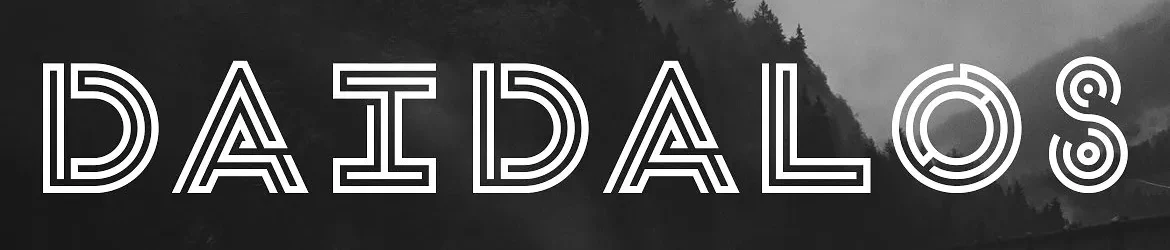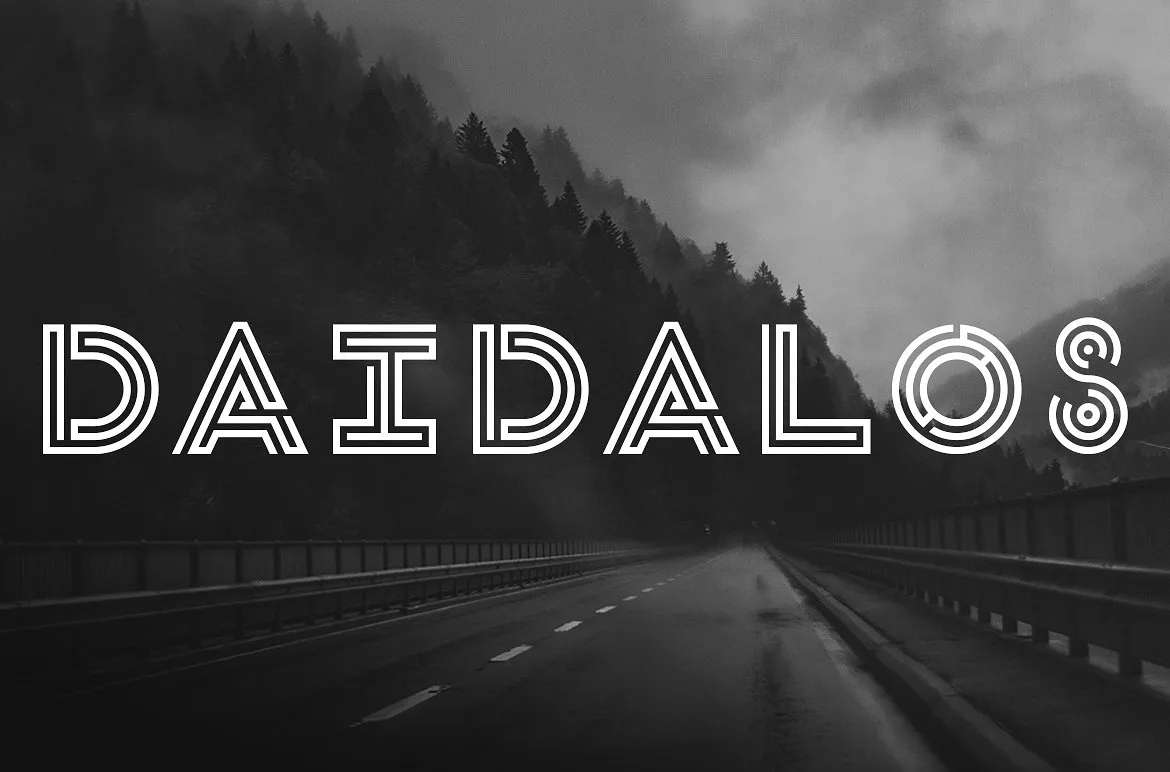
Daidalos Display Font
Aqui está uma descrição para a página de download da font ‘Daidalos Display Font’, em português brasileiro: Introduzimos uma nova fonte de exibição, a Daidalos Display Font, criada pelo designer 178-MC. Esta é uma fonte premium disponível na Creativemarket e hoje está totalmente gratuita para download. A fonte ‘Daidalos’ foi o primeiro projeto gráfico do designer, que começou casualmente e deu origem a um trabalho tão brilhante e fresco. Acreditamos que você vai encontrar muita diversão ao usar esta fonte como fizemos criando-a.